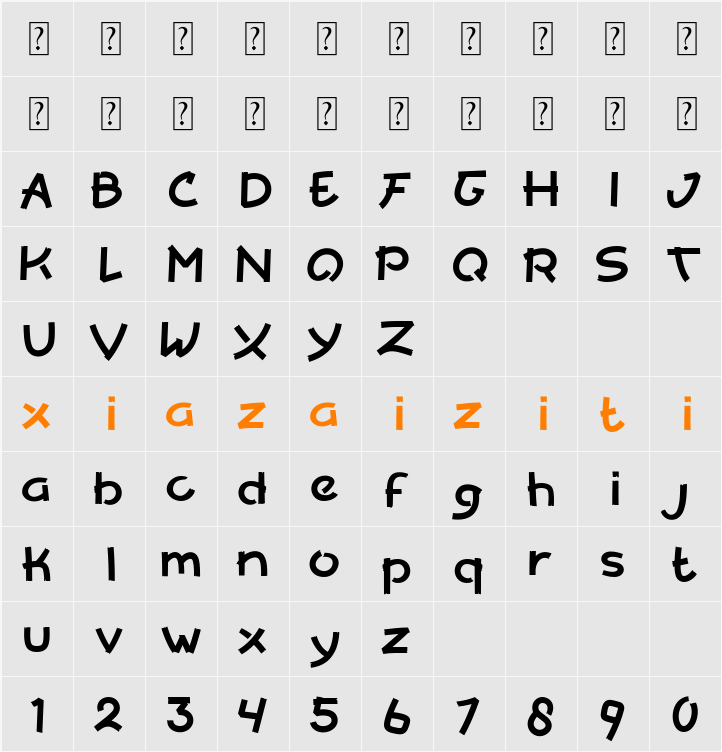
Yoruka
Yoruka,这款字体结构工整、笔画清晰,兼顾美观与易读性,适用于标题、正文、海报、包装、LOGO 等多种场景。字形优雅稳定,风格百搭耐看,适配日常排版与创意设计,让文字呈现更舒适、更具质感。Yoruka一笔一画,皆是细节,以均衡的比例、流畅的线条打造舒适视觉体验,字形端正大气,风格简约现代。无论是商业设计、品牌宣传还是日常排版,都能轻松驾驭,让文字更有格调与力量。Yoruka字体下载。